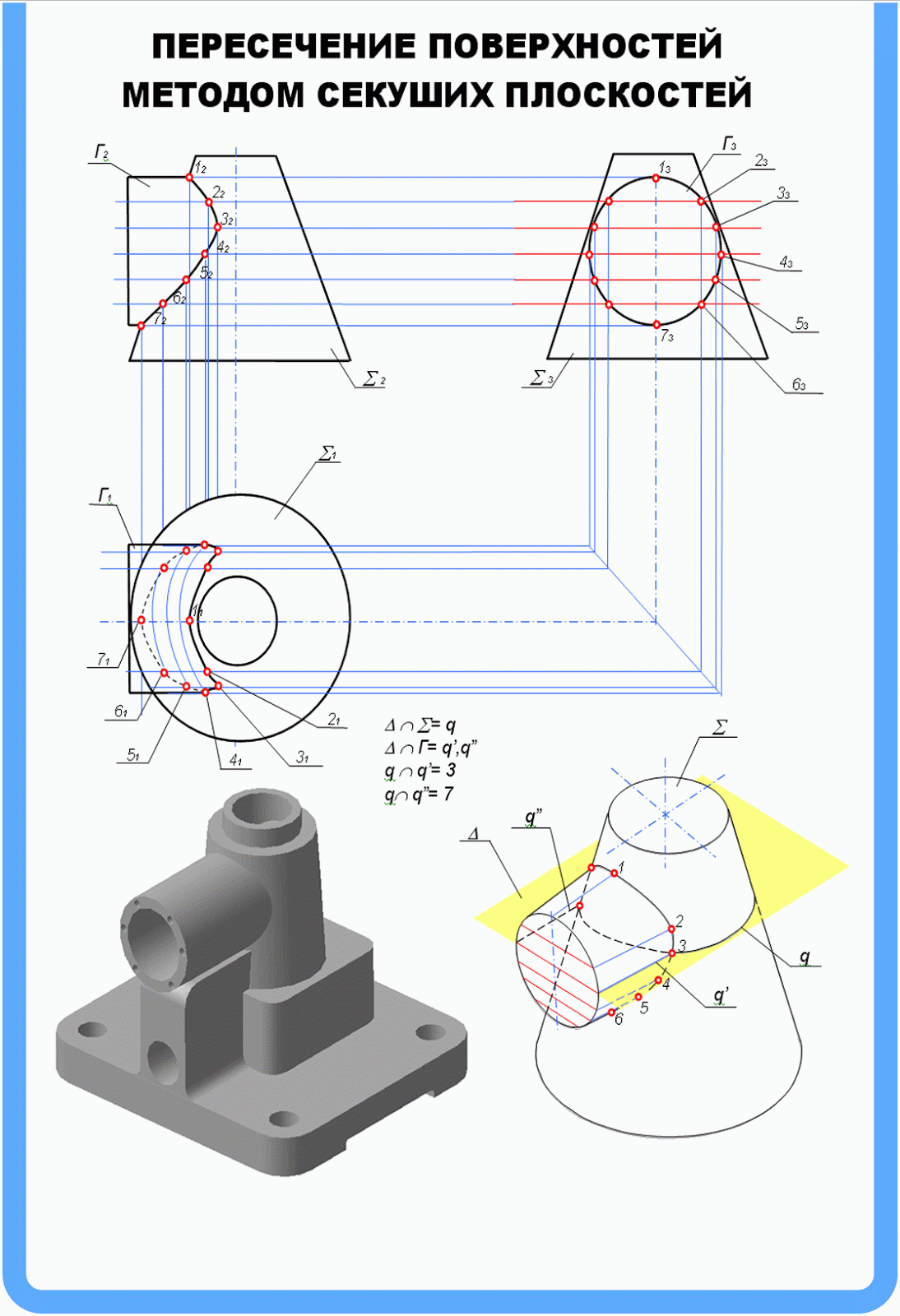
Как выбрать правильный шрифт для чертежей и проектов инженерной графики
Этот раздел включает рекомендации по выбору и использованию шрифтов в начертательной геометрии и инженерной графике. Мы расскажем о самых подходящих шрифтах для точных чертежей, а также дадим советы по улучшению визуального восприятия чертежей с использованием правильных типографических решений.
Для начертательной геометрии рекомендуется использовать шрифты с прямыми, четкими линиями, такие как ISO или GOST, для обеспечения точности и легкости восприятия информации.
Избегайте использования декоративных шрифтов, так как они могут затруднить восприятие чертежей и снизить их информативность, особенно на мелких масштабах.
Обратите внимание на размер шрифта. Для чертежей обычно используется размер 3-5 мм, чтобы текст был хорошо виден и читаем на различных масштабах.
Для мелких деталей чертежа используйте шрифт с узкими и компактными символами, чтобы сохранить четкость текста при уменьшении масштаба.
При работе с многостраничными чертежами применяйте один и тот же шрифт на всех страницах для сохранения единства и профессионального вида проекта.
Следите за контрастом между шрифтом и фоном. Белый текст на черном фоне или темный текст на светлом фоне улучшает читаемость и визуальную ясность.
Используйте стандартные шрифты, такие как Arial, Calibri или более специализированные, чтобы избежать проблем с совместимостью и отображением на разных устройствах и программах.
При создании чертежей с текстом избегайте перегрузки шрифта, чтобы оставить достаточно пространства для других элементов и сохранить баланс на изображении.
Для важной информации, такой как размеры или обозначения, используйте шрифт с большей толщиной или подчеркнутый стиль, чтобы выделить ключевые данные.
Проверяйте чертежи на читаемость, особенно при увеличении или уменьшении масштаба, чтобы убедиться, что все элементы текста остаются четкими и разборчивыми.